収録されているのは、「闘龍」と「陽炎」の二種類。
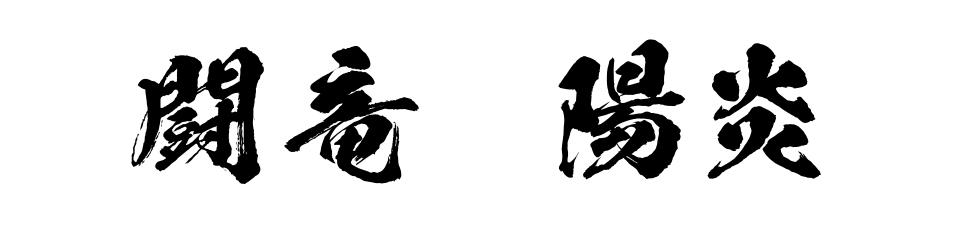
力強く、使っているだけでかっこよく見えそうなフォントですが、
確かに、いつ使うのか疑問も残ります。。🤔
祭りとか。。?
とりあえず、衝動買いしてしまったので、
今の心の声を書いてみました。。
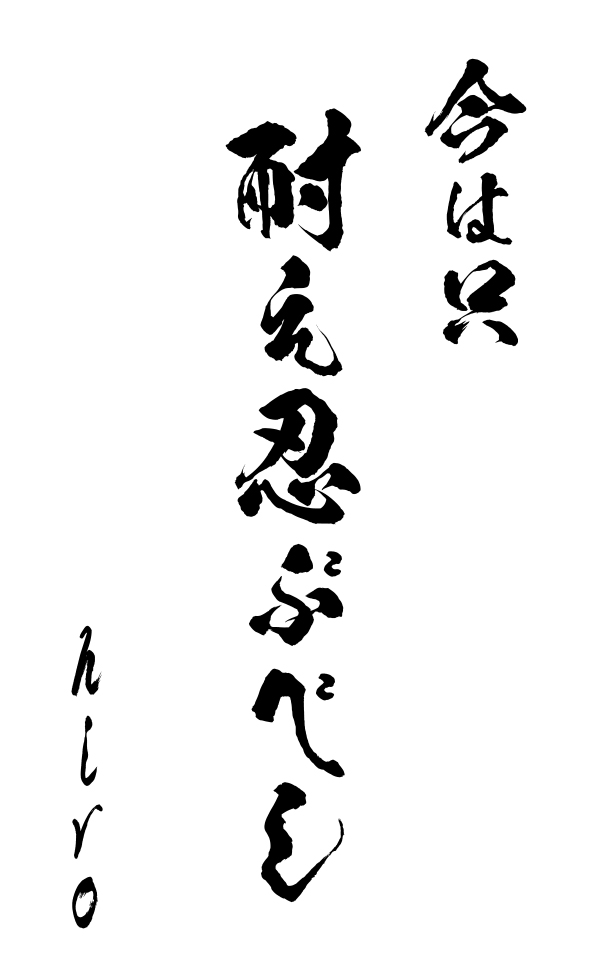
漢字を少し大きめにして、
文字間を詰めてあげると少しぽくなるのかなと。。